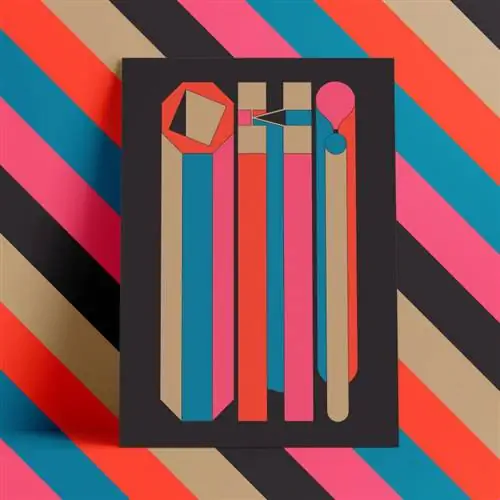
Авантюрный, графичный, веселый и громкий, Ragtag - это новый дисплейный шрифт от In-House International и первый шрифт, выпущенный студией дизайна из Техаса.
Каждая буква уникальна и разработана таким образом, что она «красиво сочетается со всеми остальными», но может «также стоять сама по себе в качестве акцента или части дизайна», - говорит Мичу Бенаим Штайнер, креативный директор начальник американской фирмы.
Ragtag содержит три набора глифов (от A до Z, 0-9), а также несколько дополнительных элементов, таких как eñes и диакритические знаки. Внутренний партнер Александр Райт нарисовал отдельных персонажей, чтобы они могли «стоять сами по себе, как каждый из них мог бы быть логотипом, но с учетом композиций и системы."
Шрифт был вдохновлен «разрозненной командой производителей и дизайнеров» в дизайн-студии, которая представляет собой полностью удаленный творческий дом в Остине. Ragtag также знаменует собой запуск литейного производства студии, уделяющего особое внимание жирным шрифтам для дисплеев.